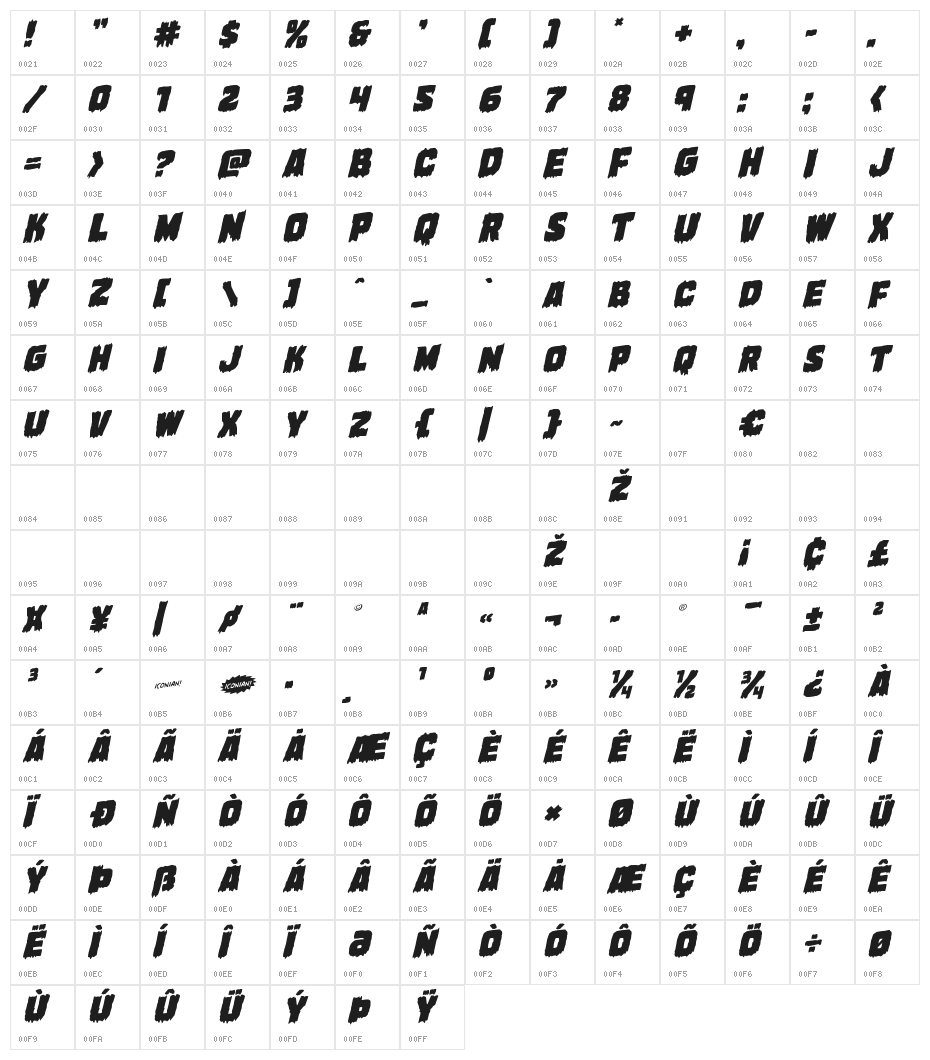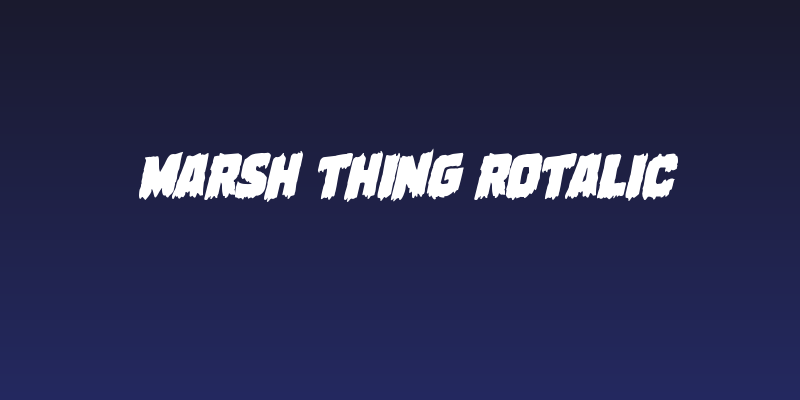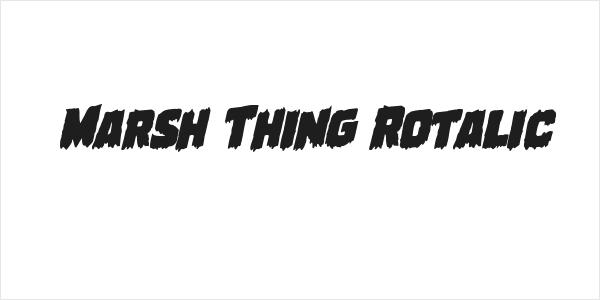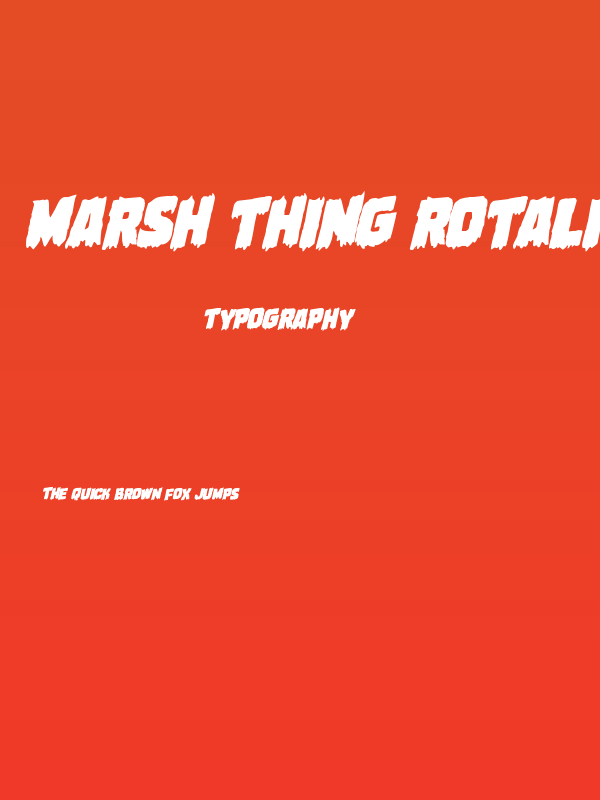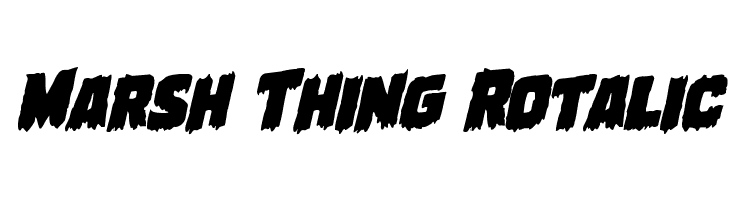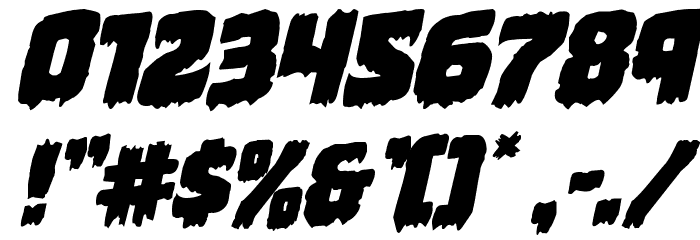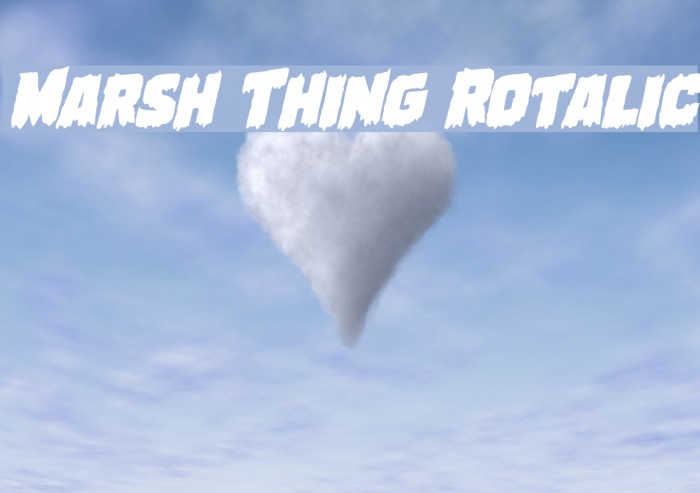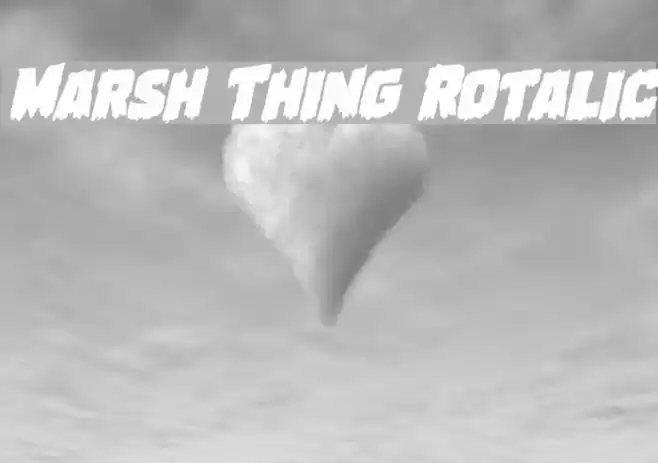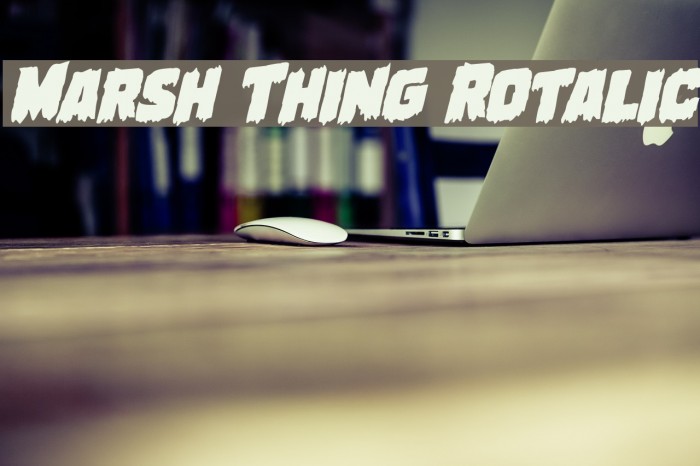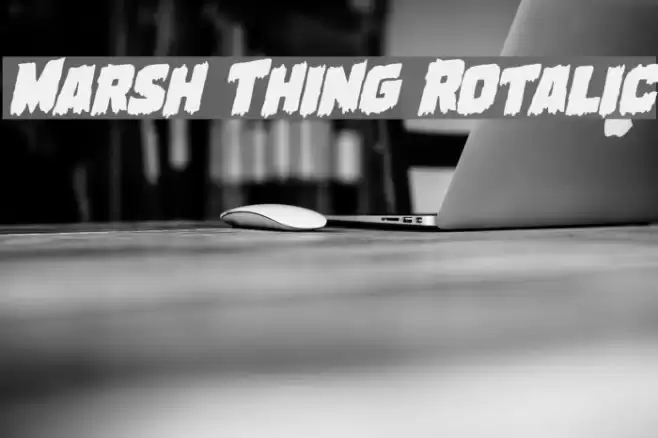
Marsh Thing Rotalic Font
✎ Horror
| Projetos propostos | Ideal for horror movie posters, action-themed graphics, Halloween event flyers, and video game titles. |